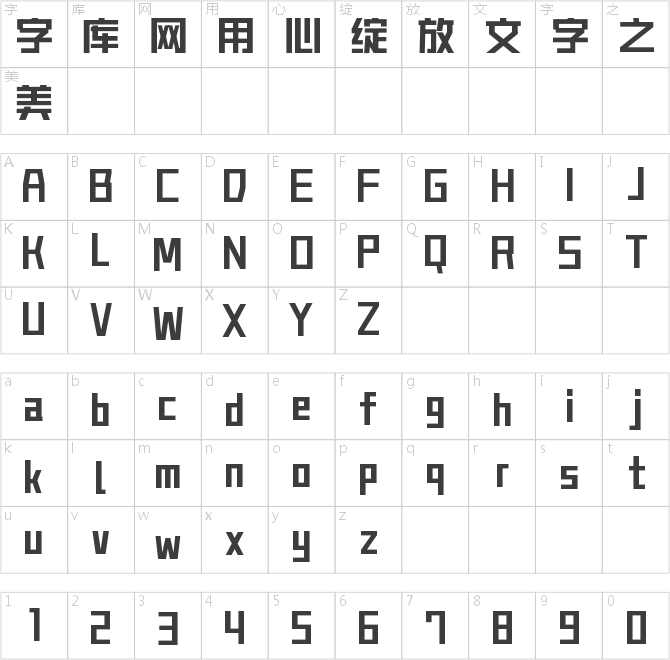
字体名称: 华光钢铁直黑_
华光钢铁直黑_可变体
华光钢铁直黑_可变体 是一套可以自由变换粗细的GB2312字体。在PS和AI2018CC以上版本可直接使用。平直的笔画,规整的线条,扎实的结构,方正的字形,此套字体表现出刚正不阿、一丝不苟的品质。适用于广告杂志、标题标语、影视包装网页设计等场景。
华光钢铁直黑_可变体字体华光钢铁直黑VF可变体字库是一款让人赏心悦目、百看不厌的中文字体,适合各类广告和产品包装设计应用,字体大小2.21MB,格式为ttf字体,上传用户是13226568769,作者/版权方为华光字库